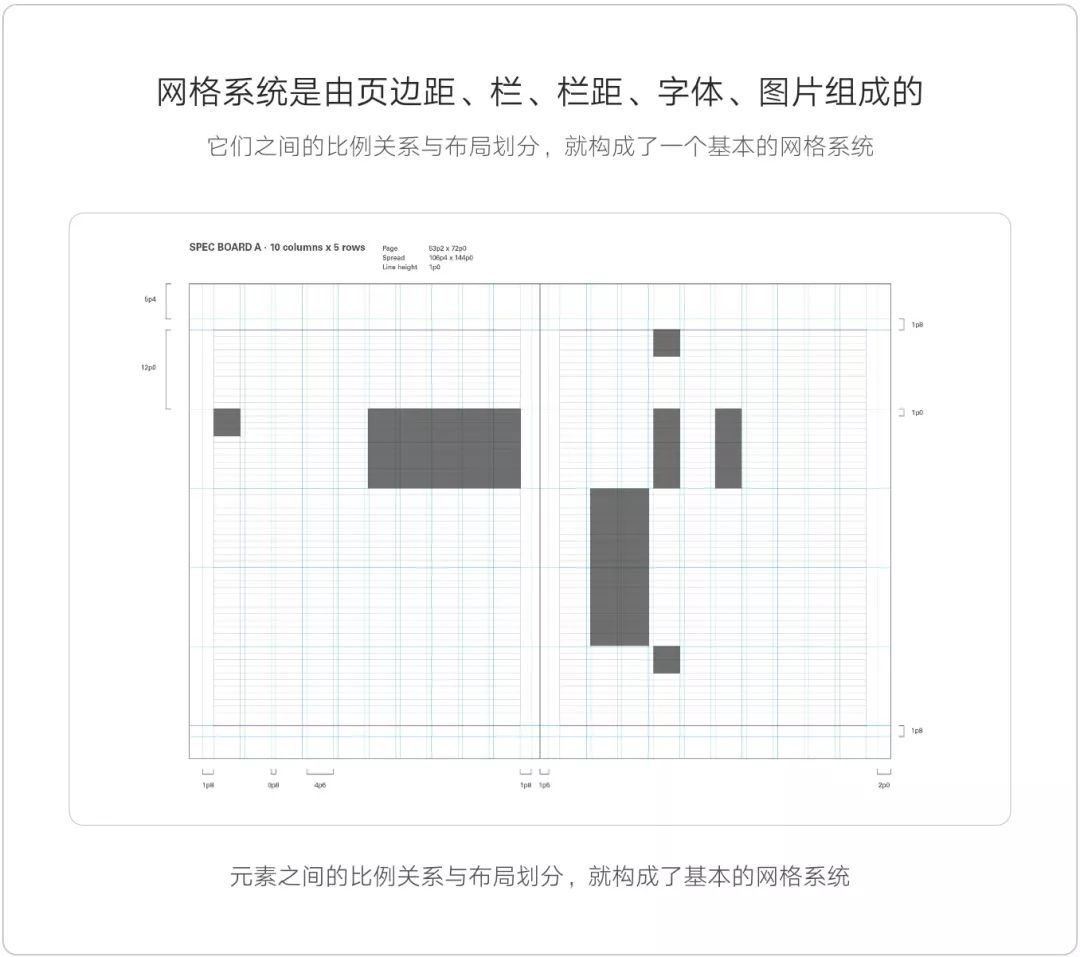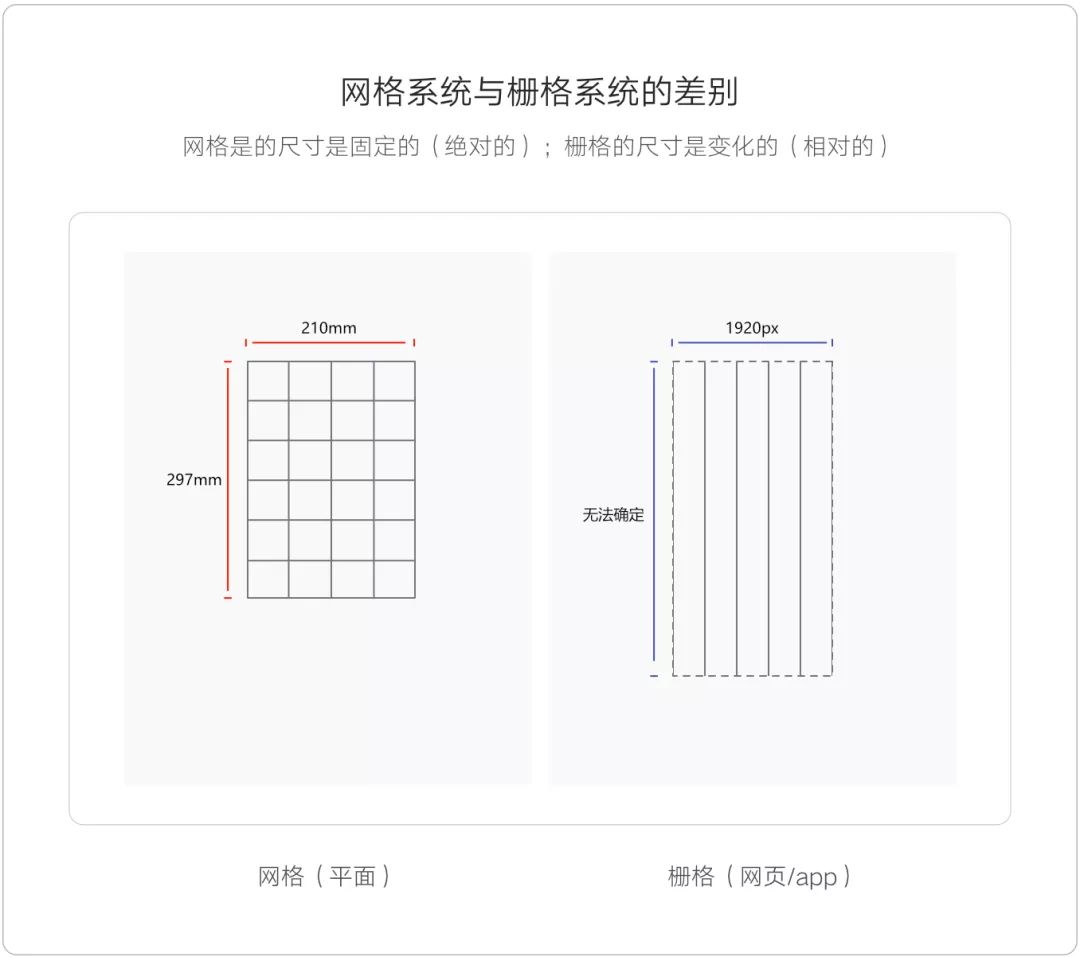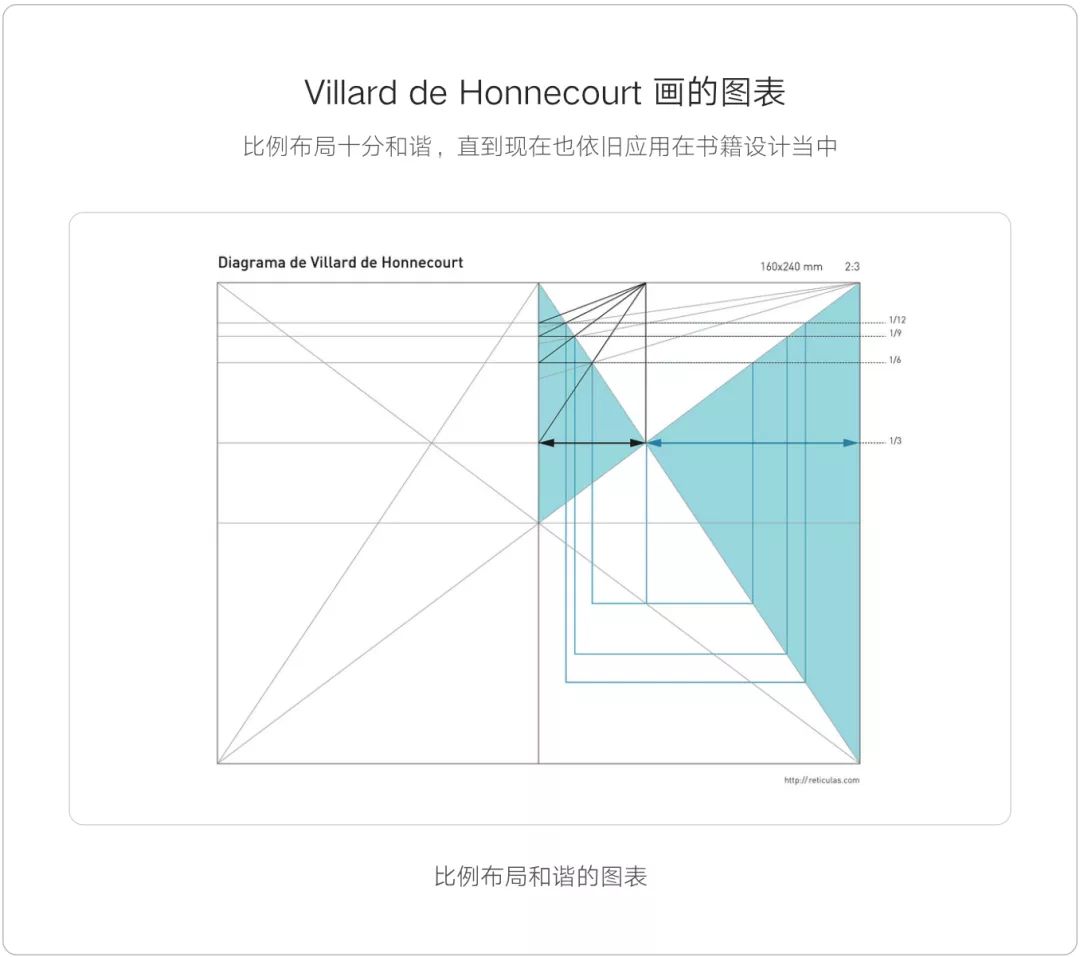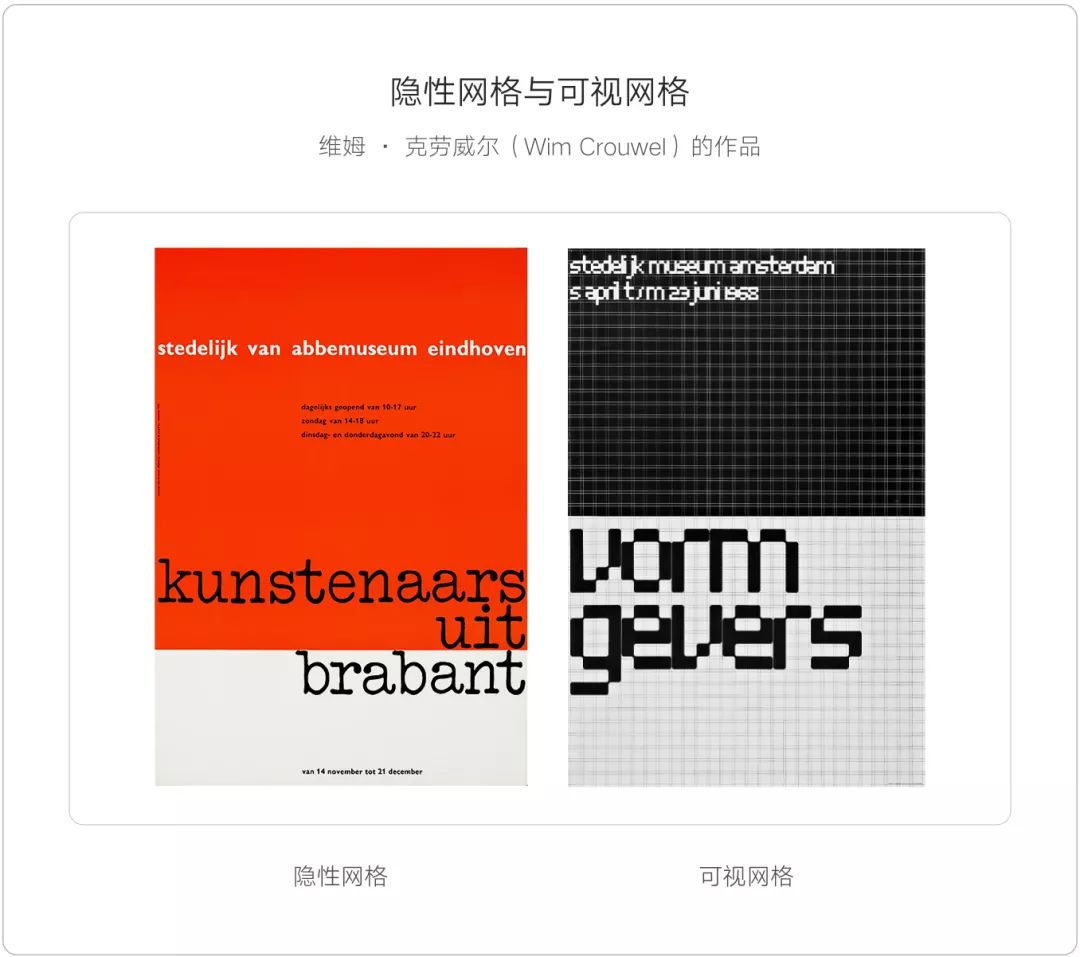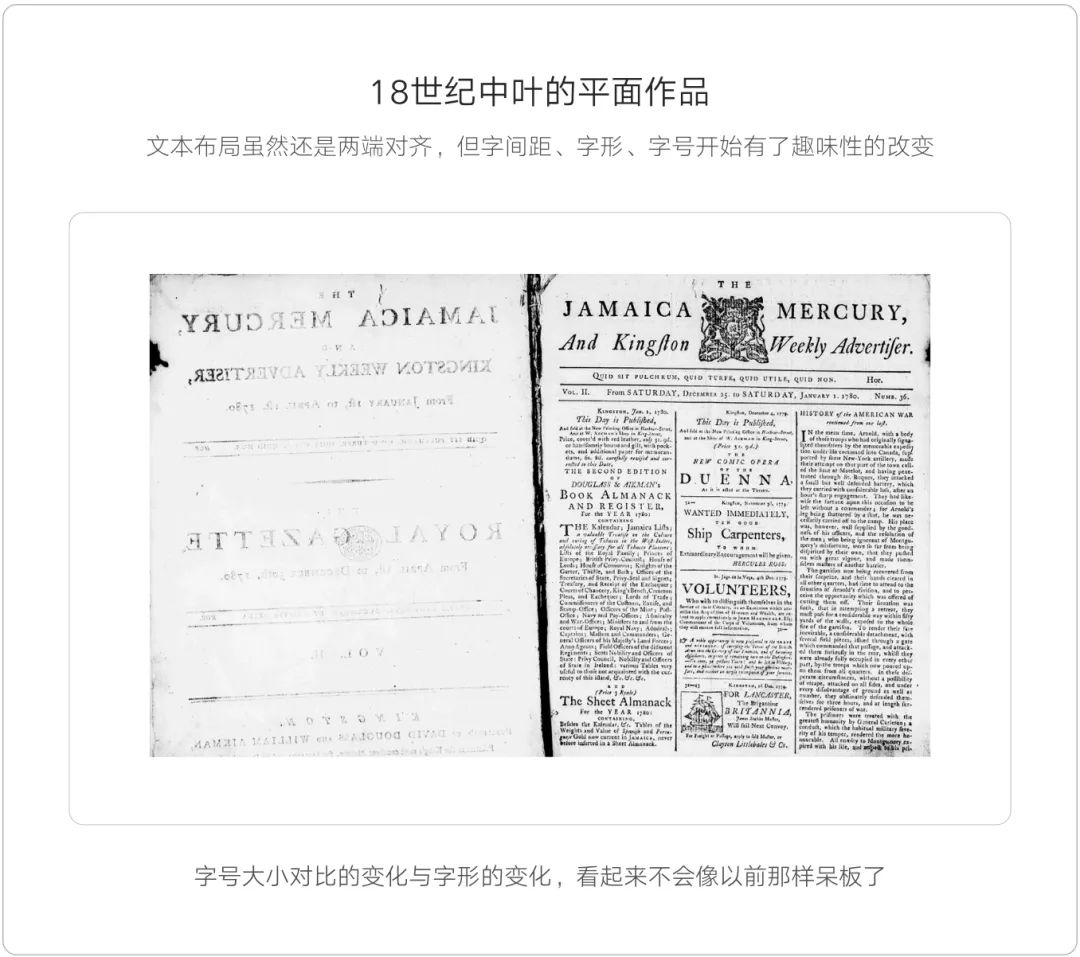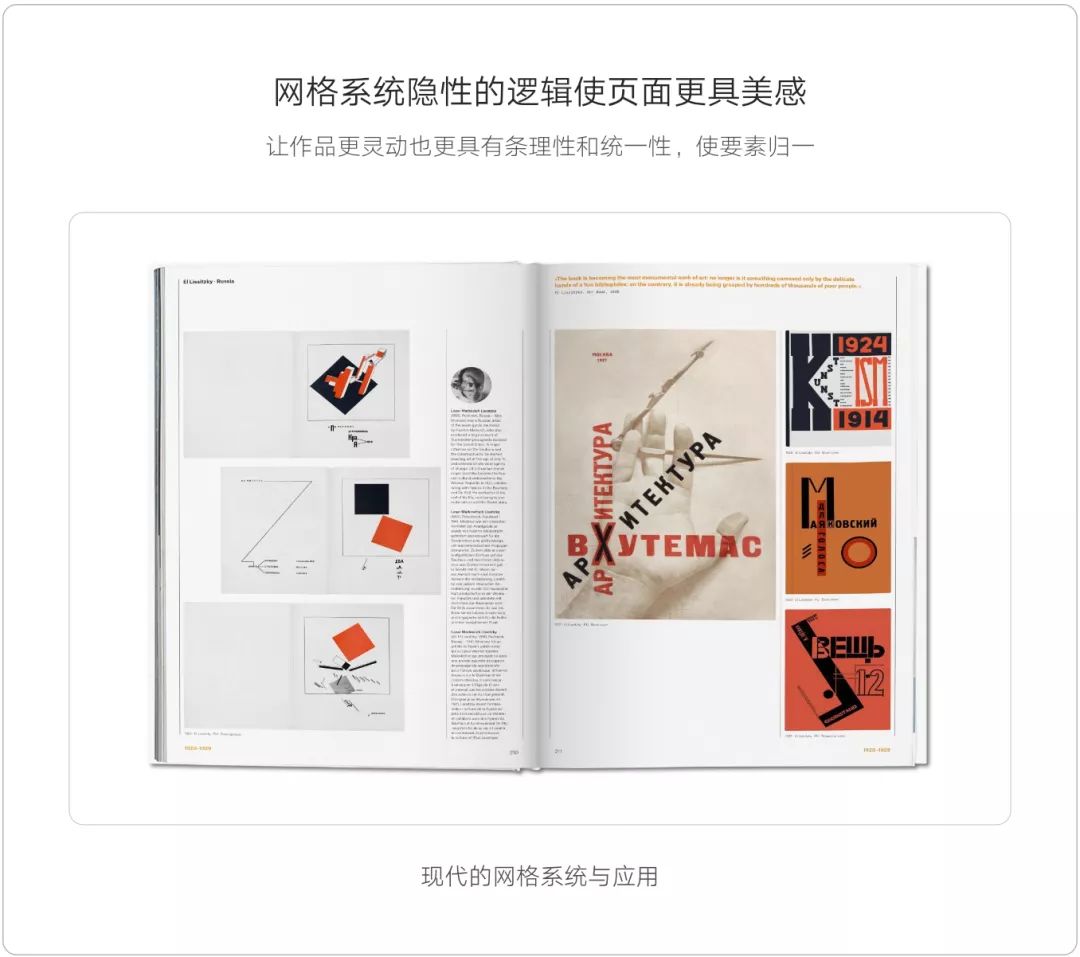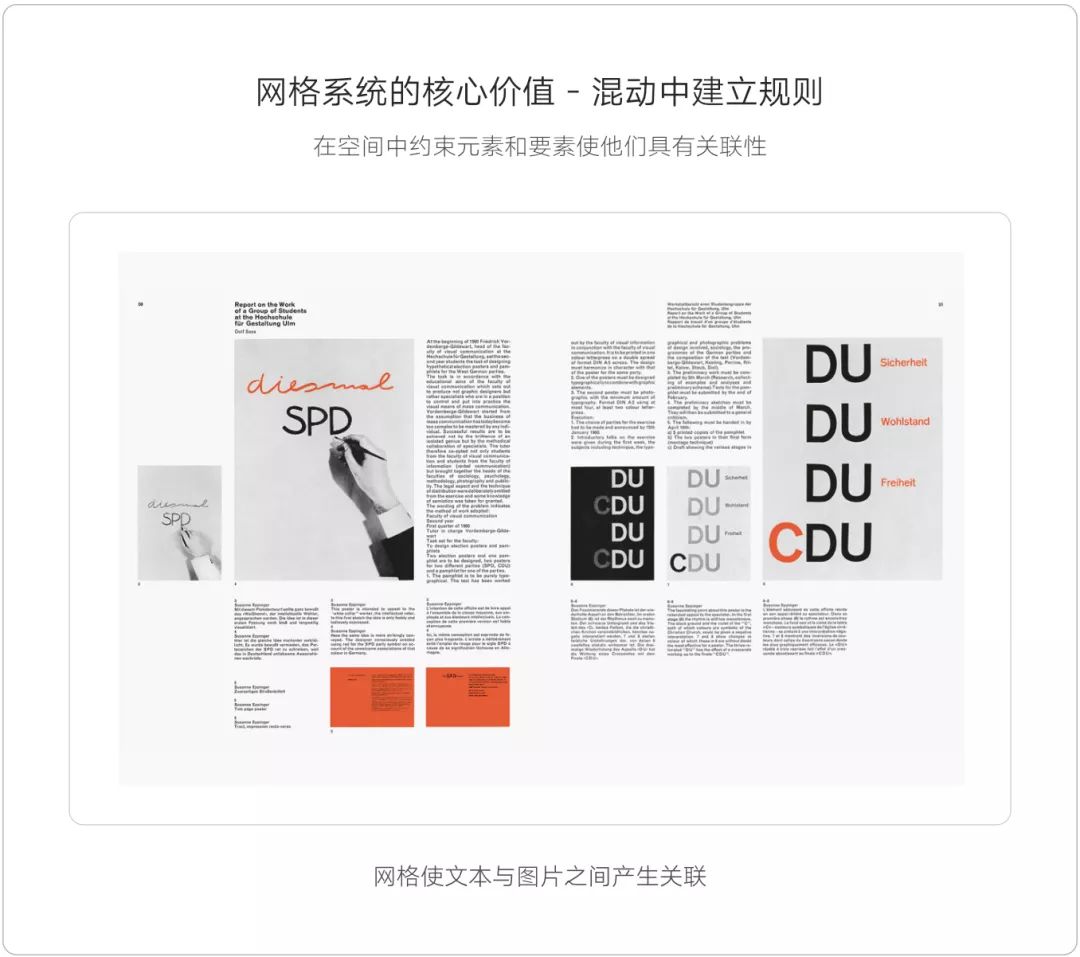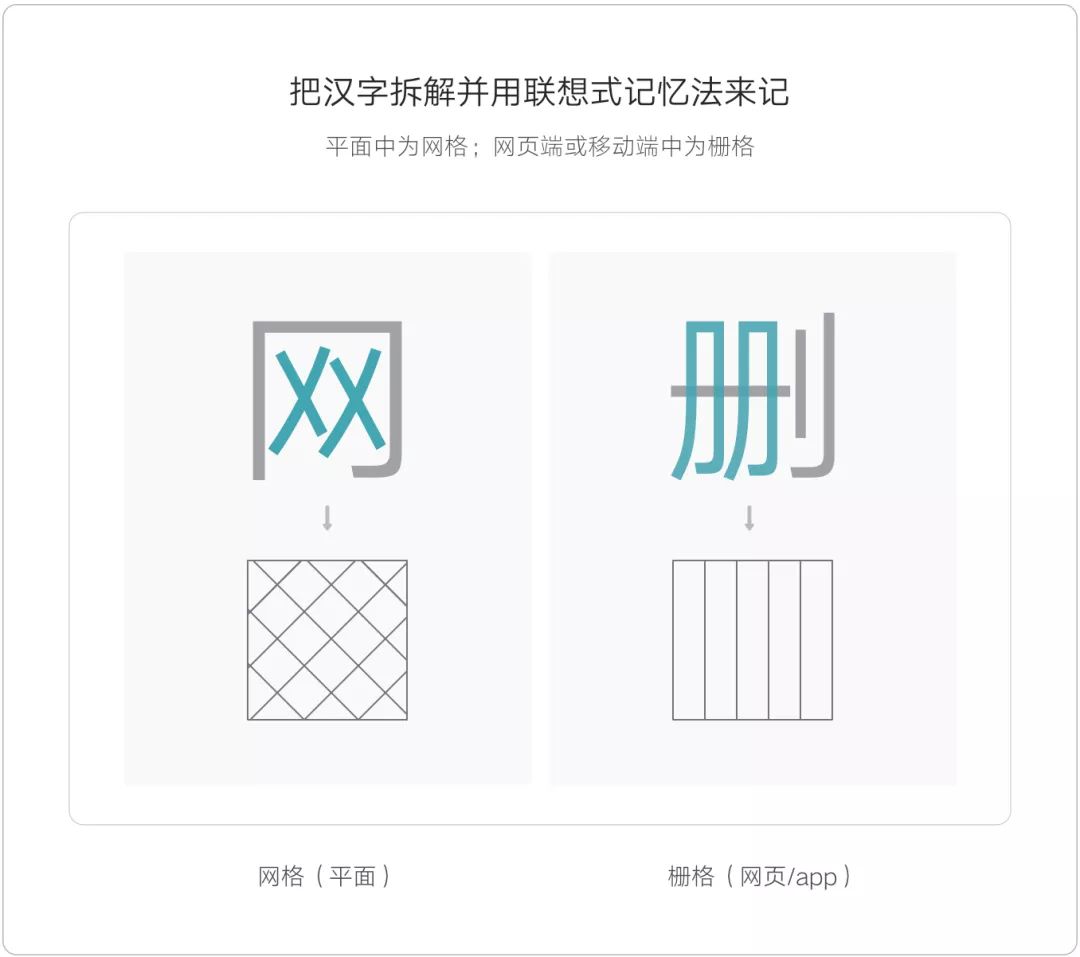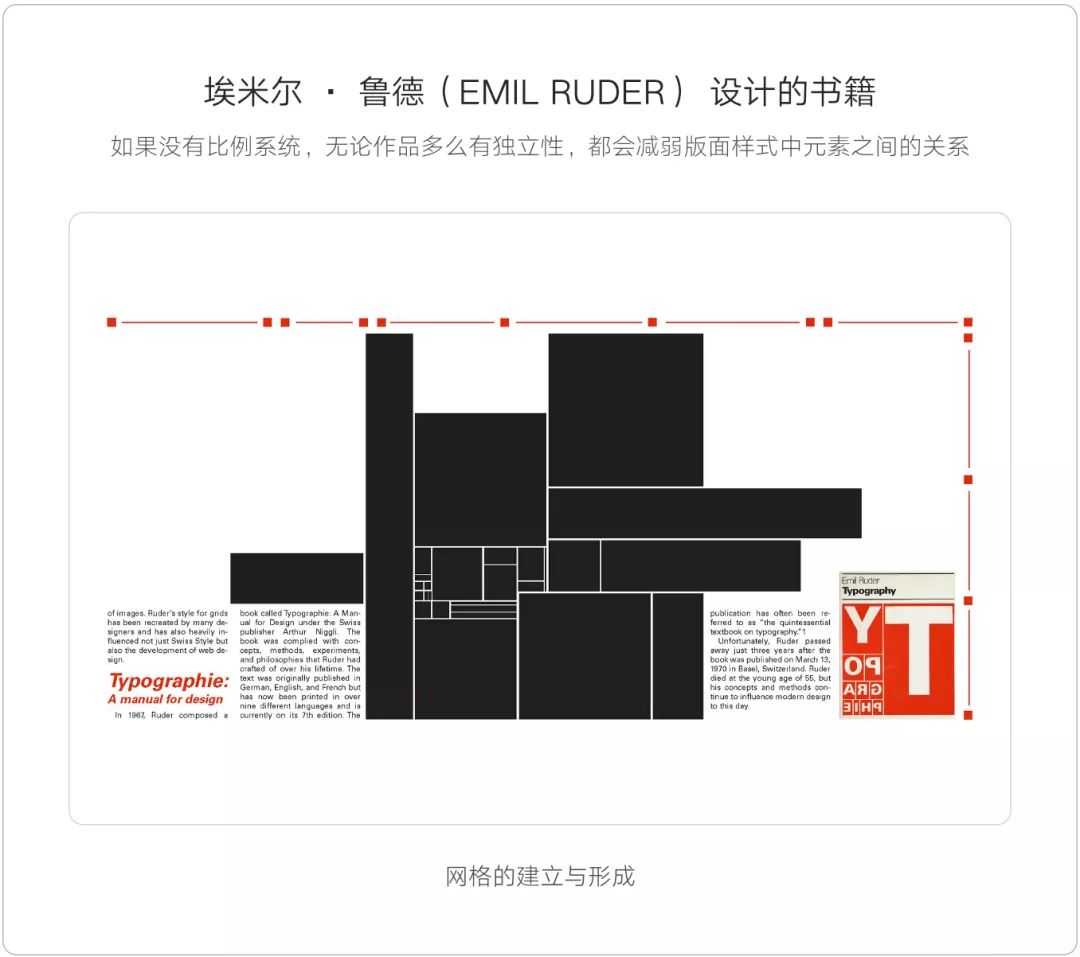
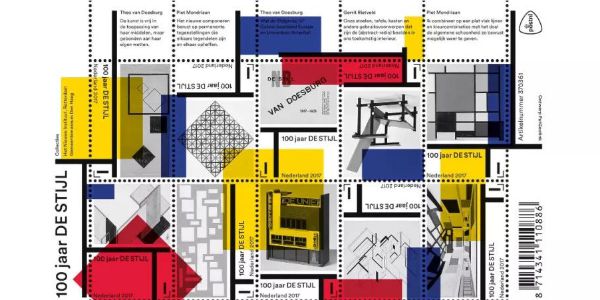
一篇文搞懂网格的前世今生
网格系统的框架也是非常的庞大,从网格的历史,规则、解构网格等,都是需要去学习的知识, 也请大家认真学习吧。
01
什么是网格
网格系统是由页边距、栏、栏距、字体、图片、元素间距组成的,它们之间的比例关系与布局划分,构成了一个基本的网格系统。基本的网格尺寸必须满足易读性的要求,要让观众可以阅读并容易阅读。网格中所有元素的尺寸和位置都是由心理学以及美学所决定的,字体的大小是由不同层级的标题和正文决定的。
通常一列的宽度的不会超过9个英文单词(具体需求具体分析),虽然说将这些词组归纳成组块太过规整,但为了确保单词的可读性,就有必要这么做了。
02
把控好网格
对于设计师来说,网格系统十分复杂且很难把控,尽管如此大多数设计师还是很偏爱它的。设计是个偏灵感且随意性强的工作,设计师们使用它时很容易被限制住,并使设计作品太过规整从而失去设计感,因此设计师对网格系统也是爱恨交加。
设计师要把控好网格系统,提炼出要素的灵动性,保持要素的规整性。要做到乱中有序并简中求精。
03
网格的价值
不管对于平面设计师、网页设计师、还是UI用户界面设计师,网格系统都有它存在的价值的。而网格系统的核心价值就是在“混沌中建立规则”,在空间中约束元素和要素,使他们具有关联性。
如果不去制定网格系统,整个空间会变得杂乱无章,混沌不堪,元素和要素之间无法产生关联,失去了统一性并影响美感与视觉感官的判断。
04
网格与栅格
网格与栅格的本质其实是相同的,都以英文单词“Grid”来表示。但我理解的,它们之间的差别在于“规格”上的不同。一般我在平面设计中把它称为“网格”。在网页端或移动端中称它为“栅格”。网格与栅格从汉字上来理解就是“网”和“删”的差别,大家也可以用联想式记忆法来记一下。
我们先理解一下平面设计和网页或App的差别。平面设计一般用到的纸张规格(尺寸),不管是英国、美国、日本或ISO采用的德国DIN纸张规格标准,只要是纸张全部都是固定的尺寸,宽度和高度都是固定的,也就是绝对的。而网页或App的设备尺寸不是固定的,宽度是根据设备的宽度决定的,高度则是随着内容的多少来决定的,也就是相对的。
在平面设计中,当我们画好格子后,把文本和图片填入到固定的格子当中就可以了。而网页或移动端的栅格系统,高度无法确定,就导致无法给格子配置高度值。所以网格与栅格本质上是相同的,重点就差在一个可以确定格子高度。
下图中所示,如果采用网格系统来制定网页,图中红色模块的高度一旦发生变化,所有高度都对不上,网格没什么意义了。
栅格的宽度可以随着不同设备的宽度来配置不同的数值。例如网页常用设备宽度为1920px,栅格的总宽度可以设置不同的固定宽度,如:960px、980px;1000px;1120px等,这些宽度都是固定的。而栅格的高度无法确定,就没法绘制格子并布置要素。
05
网格的历史
最早的网格原型,是13世纪由建筑设计师 Villard de Honnecourt 画的图表,其中的比例布局十分和谐,直到现在也依旧应用在书籍设计当中。
到了15世纪中叶印刷术的出现,到18世纪晚期的工业革命,印刷术主要用于印刷《圣经》。很多设计师开始用最完美的几何划分方法来确定古典书籍的版心,也就是整个页面与留白之间的关系。
如下图所示,它使用了黄金分割确定了文本的面积,也就是用黄金分割确定了版心,使用斐波那契数列确定了边距的比例。
16世纪晚期的《圣经》的手抄本。其中有一页采用了两端对齐的排版方式,文字排成两栏并以中心轴为对称轴,这种左右对齐(两端对齐)的排版规则持续了450年,当时还没有“网格”这个概念。
从这以后,通过艺术家、印刷工人、抄写员等艺术工作者对内容,形式、比例、空间的不断摸索,便慢慢形成了网格体系。18世纪中叶,工业革命开启了以资本为基础的经济形式,平面设计因此而诞生了。平面设计的任务是向有文化的人传达越来越多不同的信息,印刷需求也不断增加,设计逐渐注意竞争力。
到了19世纪末,有人开始把平面设计当成职业,并称自己为设计师,代表人物有手工艺美术的威廉 · 莫里斯,他确信形式和功能是密不可分的。后来因手工艺美术运动的影响,设计师们尝试在二维平面上表现三维空间感,并做出了进一步的探索。
06
风格派与包豪斯
1917年,荷兰建筑师、设计师、画家提奥·范·杜斯堡创立了风格派。对于网格设计而言,这一运动的重要性在于它探讨了功能决定形式,以及功能与形式之间的逻辑关系。风格主义者注重简约化,认为简单的形式是容易实现,并容易被大众接受的。只用直线的形式来表现并去除多余的装饰。
1919年,一批杰出的艺术家和设计师,在德国魏玛(曾经德国的文化中心)创建了包豪斯,由建筑师瓦尔特 · 格罗皮乌斯担任校长。他认为建筑,平面设计、工业设计、绘画、雕塑等都是相关联的,这一认识对字体和图形设计的发展产生了深远的影响。
20世纪20年代,扬 · 奇肖尔德在他的两本书中《新字体排版》(1928)和《印刷设计》(1935)阐述了他的排版原则。他认为设计师类似工程师,并认为强制性的非对称是现代主义的核心,他说应该使用“自然”而不是“形式主义”的方法来创造新的设计,那这里的“自然”我理解的“主观唯心主义”。他的作品仍然体现的是美学上的精致与动态化(动势)。
07
网格与瑞士风格
20世纪中期(第二次世界大战,1939~1945),瑞士在战争期间是中立国,战乱时不少流亡的知识分子在这里避难。那时的出版物必须使用法语、德语和意大利语三种官方语言,因此官方出版物使用了多栏的结构,采用了模块化的方法。一些瑞士艺术家、设计师在其绘画和平面中探寻逻辑与形式,并撰写关于网格方面的知识,并把这些知识称为整体性设计。
如果没有比例系统,无论作品多么有独立性,都会减弱版面样式中元素之间的关系 - 埃米尔 · 鲁德。
08
网格与教学
到了20世纪末,卡尔 · 格斯纳在1962年为杂志《丘比特》设计的网格,根据它的数学的精巧性,被认为接近完美的。网格和页面布局的不同取决于创意的灵活性和数学的精确性。要考虑开本,要考虑基线,还要考虑栏数与页编辑,线的单位也要细分的更精确(1pt或2pt)。通过电脑可以很容易把网格精确划分为更小的模块。网格可以通过很多方法组合,并在设计中仍保持凝聚力。
09
可视网格
传统网格都是隐性的,存在于作品中的逻辑规则,是不会显现出来的。但在20世纪50年代,模块化网格系统的先驱者荷兰设计师维姆 · 克劳威尔。他在1967年在阿姆斯特丹市美术馆举办的Vormgevers展览中,设计的海报和目录册的布局使用了可视的网格,网格也成为了字体设计的基础,并影响至今。现代很多艺术作品也依旧采用可视网格进行创意设计。
至今
网格系统是由前辈们的思想结合体,由前辈们不断完善并总结形成的一套体系,并影响至今。从平面设计到网页设计,再到移动端设计的演变,现已成为设计师日常工作中的一部分。网格系统能使设计作品具有较强的关联性,隐性的逻辑使页面更具美感,让作品更灵动也更具有条理性和统一性,使要素归一。